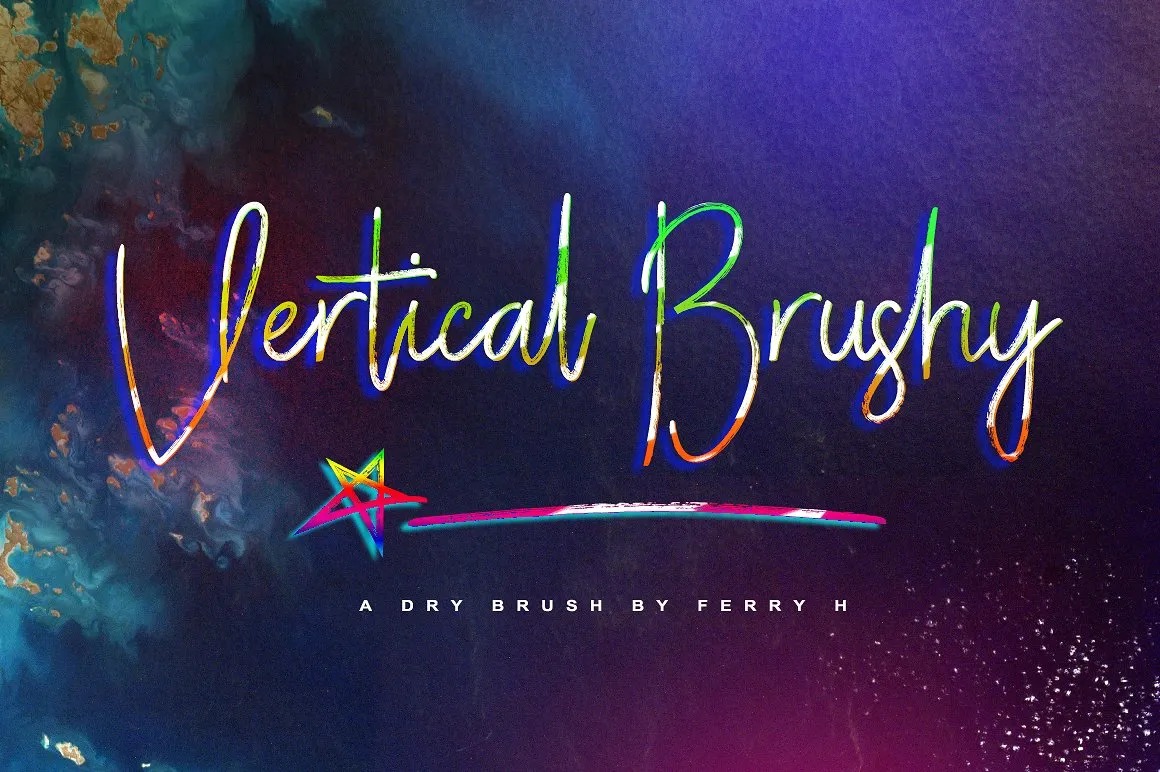
A Vertical Brushy Font é uma tipografia script ideal para quem busca um estilo único e autêntico. Desenvolvida pelo designer Ferry Hadriyan, a Vertical Brushy oferece uma experiência de escrita sem igual com sua tipologia moderna e deslumbrante. Este recurso gráfico é perfeito para design editorial, elementos de design, identidade visual em casamentos e eventos, arte para t-shirts, logotipos, brochuras, selinhos, adesivos e muito mais. Com seu estilo de traçado feito à mão em ferrão secado, a Vertical Brushy é uma escolha ideal para quem busca um visual distintivo. A fonte traz um brilho moderno e grotney no design gráfico enquanto mantém o charme autêntico do traçado à mão, garantindo que seu trabalho seja reconhecido e admirado. Esta fonte é perfeita tanto para designers profissionais quanto para iniciantes que buscam adicionar um toque de personalidade a suas criações. Com sua versatilidade e estilo único, a Vertical Brushy Font é uma ótima escolha para quem busca criar trabalhos cheios de vida e emoção.